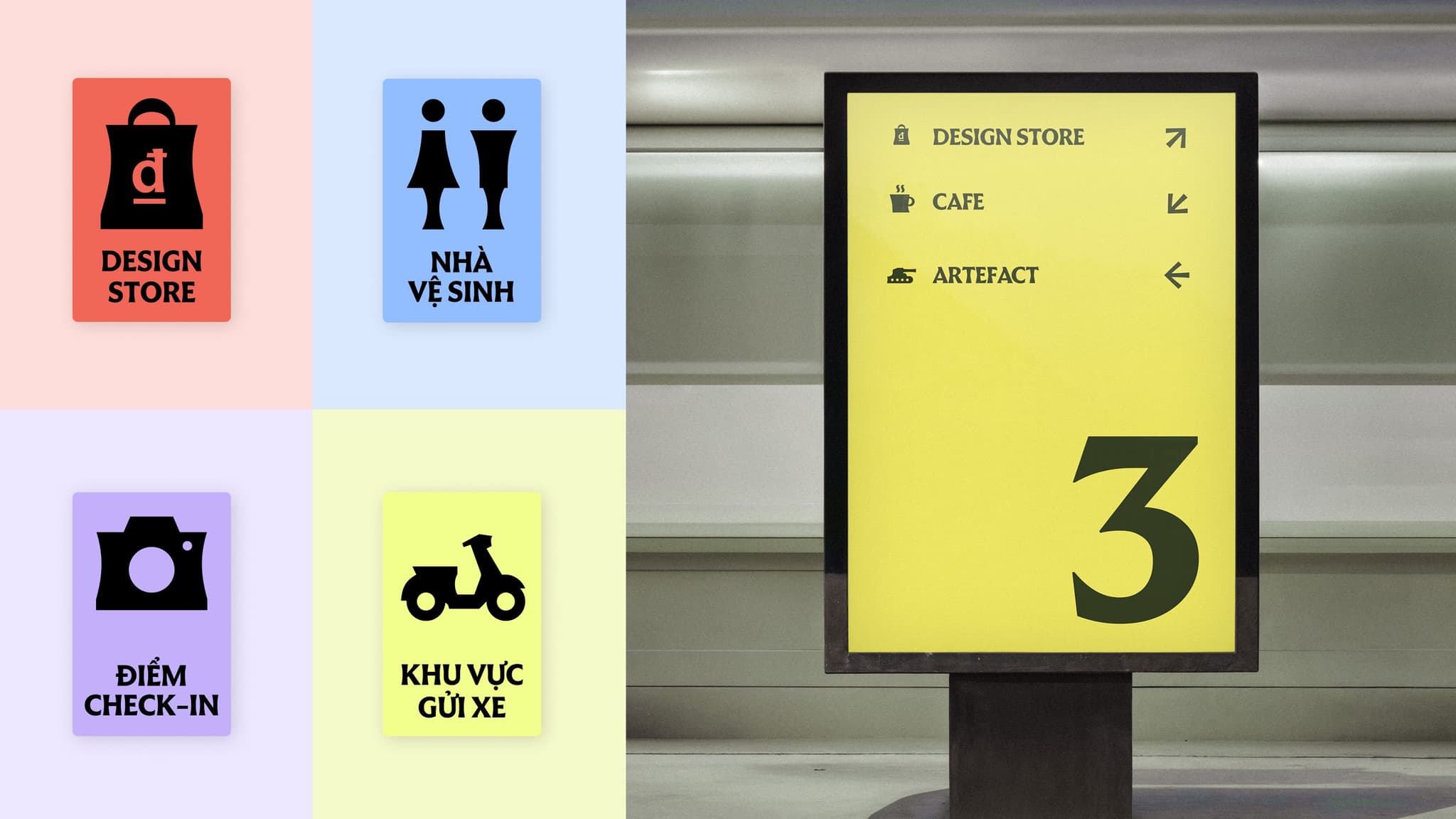
Independence: Hệ thống font chữ lấy cảm hứng từ rèm hoa đá Dinh Độc Lập
Tổng quan về font chữ Independence
Independence là một dự án typeface biến đổi (variable typeface) đầy thú vị được CDA hợp tác thực hiện cùng Dinh Độc Lập.
Lấy cảm hứng từ những mảng rèm hoa đá mang tính biểu tượng tại Dinh Độc Lập cùng triết lý “đan xen”, bộ font này đã chuyển hóa nhịp điệu kiến trúc và những khối đá thô cứng thành một ngôn ngữ thị giác đầy tính đương đại. Đây không chỉ đơn thuần là một bộ font, mà là một hệ thống chữ viết sống động, được xây dựng trên nền tảng di sản nhưng tinh chỉnh để phù hợp với hơi thở hiện đại và nhu cầu ứng dụng thực tế.
Cảm hứng từ chất liệu đến ý nghĩa
Font chữ này được chắt lọc từ chính những họa tiết rèm hoa đá, lớp “áo” bằng đá bao bọc tầng hai của Dinh. Thông qua những khung lưới tựa như ống tre, kiến trúc sư Ngô Viết Thụ đã khéo léo đan cài ngôn ngữ nghi lễ của kiến trúc cung đình Huế vào một biểu tượng hiện đại ngay giữa lòng Sài Gòn.
CDA đã chuyển đổi logic kiến trúc ấy thành ngôn ngữ typography: nhịp điệu, các lớp, độ tương phản và sự tiết chế. Từ những viên đá được sắp đặt, một ngôn ngữ thị giác mới đã hình thành.
DNA của Dinh Độc Lập trong từng nét chữ
Mỗi ký tự (glyph) trong bộ Independence đều mang “gen” kiến trúc của rèm hoa đá. Độ tương phản, các điểm kết thúc (terminals) và độ sâu của nét serif được căn chỉnh cẩn thận để mang lại sự rõ ràng, nhịp điệu và cấu trúc vững chãi. Đặc biệt, các dấu tiếng Việt được thiết kế như một phần không thể tách rời của hệ thống ngay từ đầu, đảm bảo khoảng cách tối ưu cho các tiêu đề (headlines) thanh thoát hay các đoạn văn bản cần sự tự tin, sắc sảo.
Biến Monument thành chuyển động
Independence được xây dựng như một hệ thống variable type với hai trục chính: trọng lượng (weight) và nét chân (serif). Sự kết hợp này giúp font chữ linh hoạt chuyển đổi, từ các văn bản chức năng (text settings) cần sự bình ổn, đến các biểu hiện tiêu đề cần độ tương phản cao mà vẫn giữ vững giọng điệu xuyên suốt trên các ấn phẩm, biên tập, biển bảng hay giao diện.
Kết hợp cùng hệ thống icon
Không dừng lại ở typography, dự án còn phát triển một hệ thống icon tùy chỉnh để hỗ trợ trải nghiệm dẫn đường (wayfinding) tại Dinh Độc Lập. Các icon này thừa hưởng trực tiếp ngôn ngữ thị giác của Independence, từ sự tương phản giữa nét dày – mỏng đến các cấu trúc hình khối.
Khi kết hợp icon với font chữ, hiệu ứng thị giác mang lại rất ấn tượng. Cả hai cùng chia sẻ các motif thiết kế và hình học từ rèm hoa đá, giúp hệ thống biển bảng và văn bản hòa quyện thành một tiếng nói chung xuyên suốt toàn bộ không gian.
Mang di sản vào cuộc sống
Independence được tạo ra để vượt khỏi giới hạn của những bộ nhận diện thông thường và đi vào đời sống. Theo triết lý “Nice & Right” của CDA, di sản không chỉ là những thứ cần bảo tồn, mà là nguồn sống cần được tiếp nối thông qua việc sử dụng hàng ngày. Được thiết kế như một công cụ chia sẻ cho các designer, nghệ sĩ, nhà nghiên cứu và những người sáng tạo tương lai, Independence mở ra không gian để biểu đạt văn hóa Việt Nam theo cách riêng của nó.